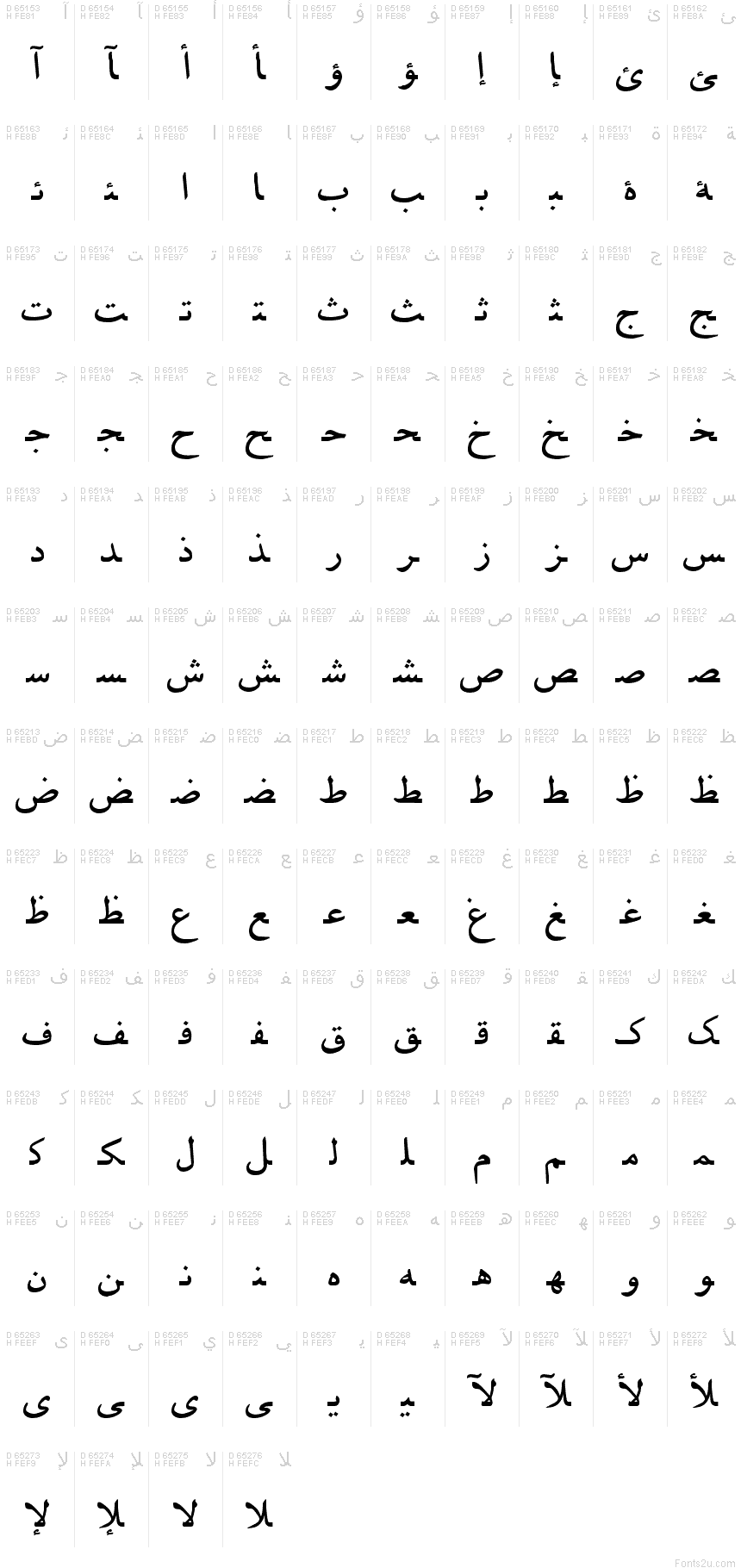
B Mashhad Bold to darmowy arabski krój typu display od Borna Rayaneh o gęstym, kaligraficznym rytmie, zakorzenionym w liternictwie prasowym i szyldach. Pociągnięcia łączą się w zwartą, stabilną teksturę, a zaokrąglony ruch i zdecydowana grubość nadają literom solidny, konkretny charakter.
Krój ten sprawdza się w redakcyjnych nagłówkach, plakatach kulturalnych, szyldach, okładkach książek i tytułach, gdzie liczy się siła arabskiego wyrazu, a nie zdobnictwo. Jako darmowy font, nadaje się również do oznaczeń na opakowaniach i krótkich haseł brandingowych, ponieważ pogrubione, połączone formy tworzą solidny blok tekstu, który brzmi pewnie i bezpośrednio.
Mapa znaków czcionki B Mashhad Bold
Mapa znaków czcionki B Mashhad Bold: Arabskie formy prezentacyjne-B, strona 1
Glify czcionki B Mashhad Bold — Arabskie formy prezentacyjne-B, strona 1